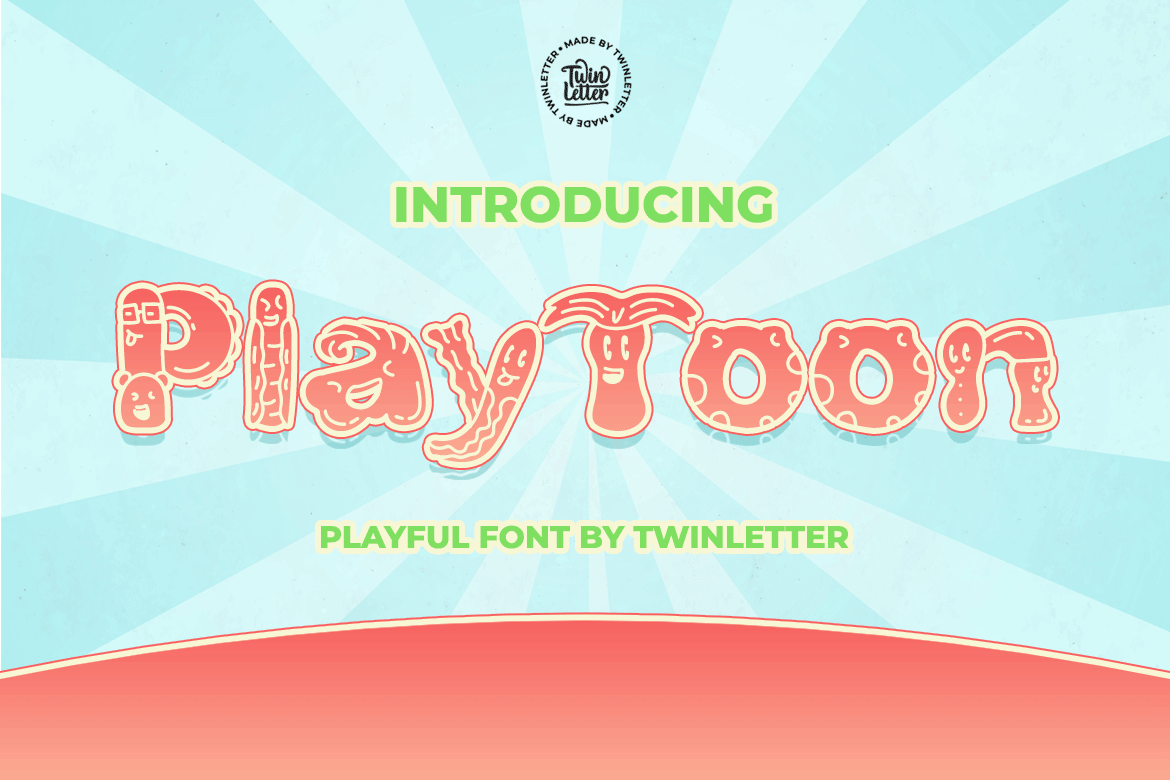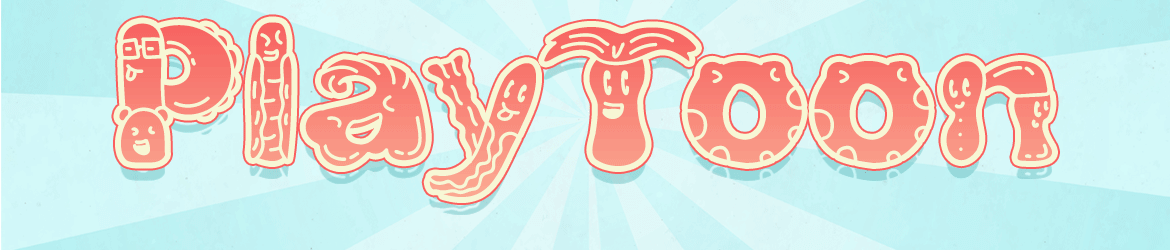
A Playtoon Font é uma deliciosa tipografia para projetos visuais que encantam com sua personalidade animada e distintiva. Cada letra foi cuidadosamente concebida para destacar um gênio único, brincalhão e autêntico. Além disso, cada uma das letras conta com um padrão inovador, intensificando ainda mais a diversão e o encanto de qualquer projeto que ela perfila. Seja você desenvolvendo um logotipo criativo para uma marca jovial ou simplesmente quer tornar seus materiais digitais mais divertidos e distintivos, a Playtoon Font certamente fará sua escolha. Experimente-a agora para agregar vida e personalidade ao seu trabalho!